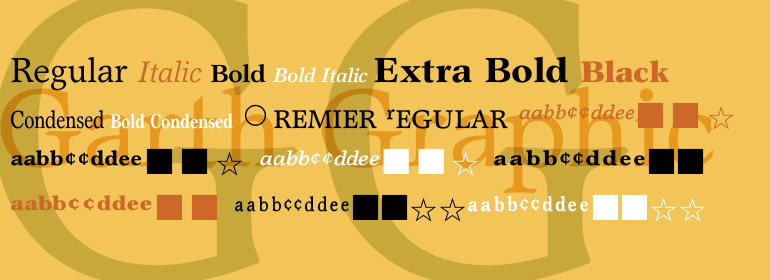
Garth Graphic®
Garth Graphic字体家族由Compugraphic Corporation于1979年发布,它是基于20世纪60年代John Matt的设计,并由Renee LeWinter和Constance Blanchard进行了重新设计。Garth Graphic以Compugraphic的创始人Bill Garth的名字命名。相当粗壮的老式风格字体比较适合文本设置;较粗的字重和细窄的形式最常用于显示工作。
Released by the Compugraphic Corporation in 1979, the Garth Graphic font family is based on a design by John Matt from the 1960's, reworked by Renee LeWinter and Constance Blanchard. Garth Graphic was named after Bill Garth, a founder of Compugraphic. A fairly strong old style face suitable for text setting; the heavier weights and condensed forms are most used for display work.